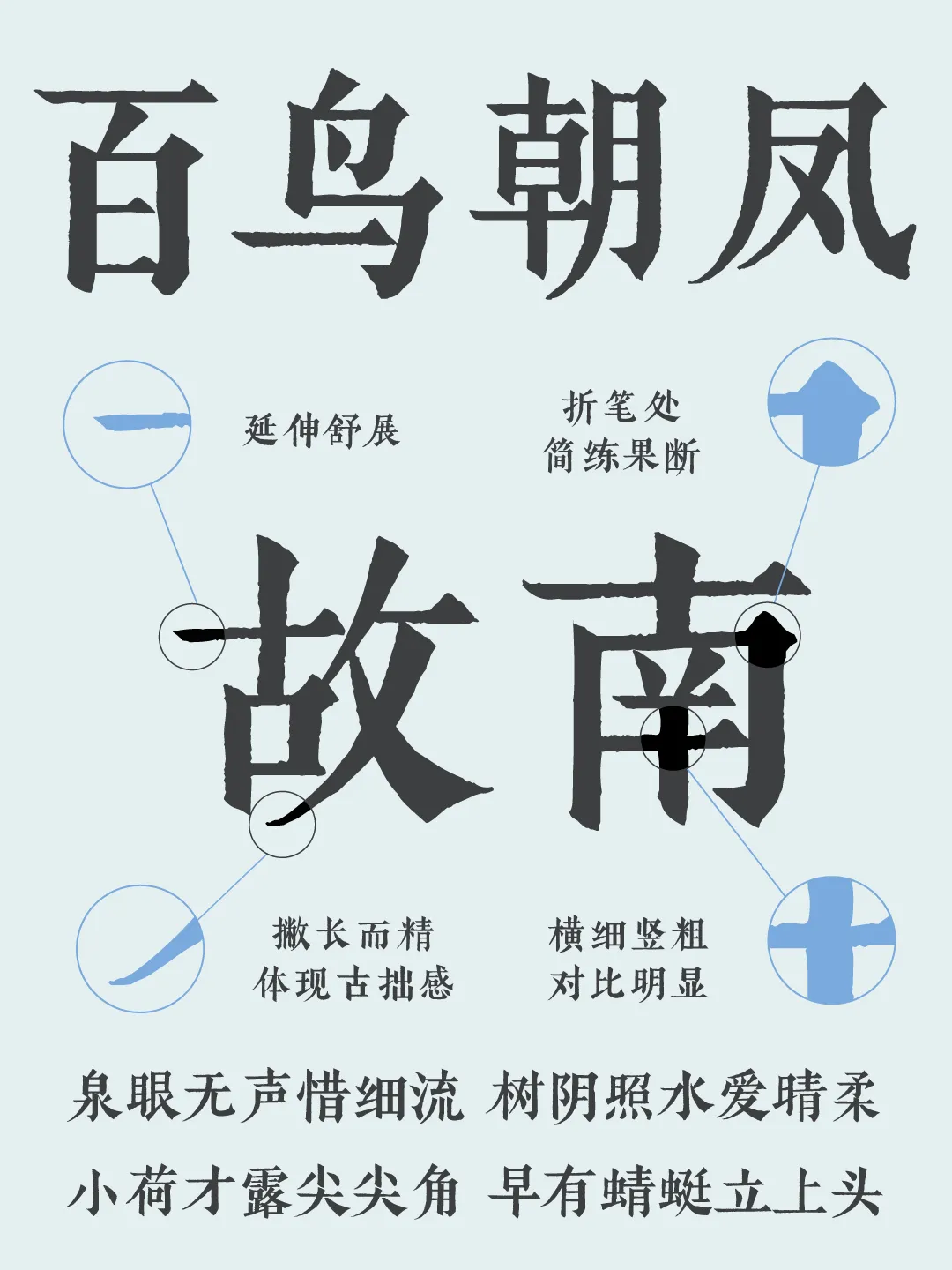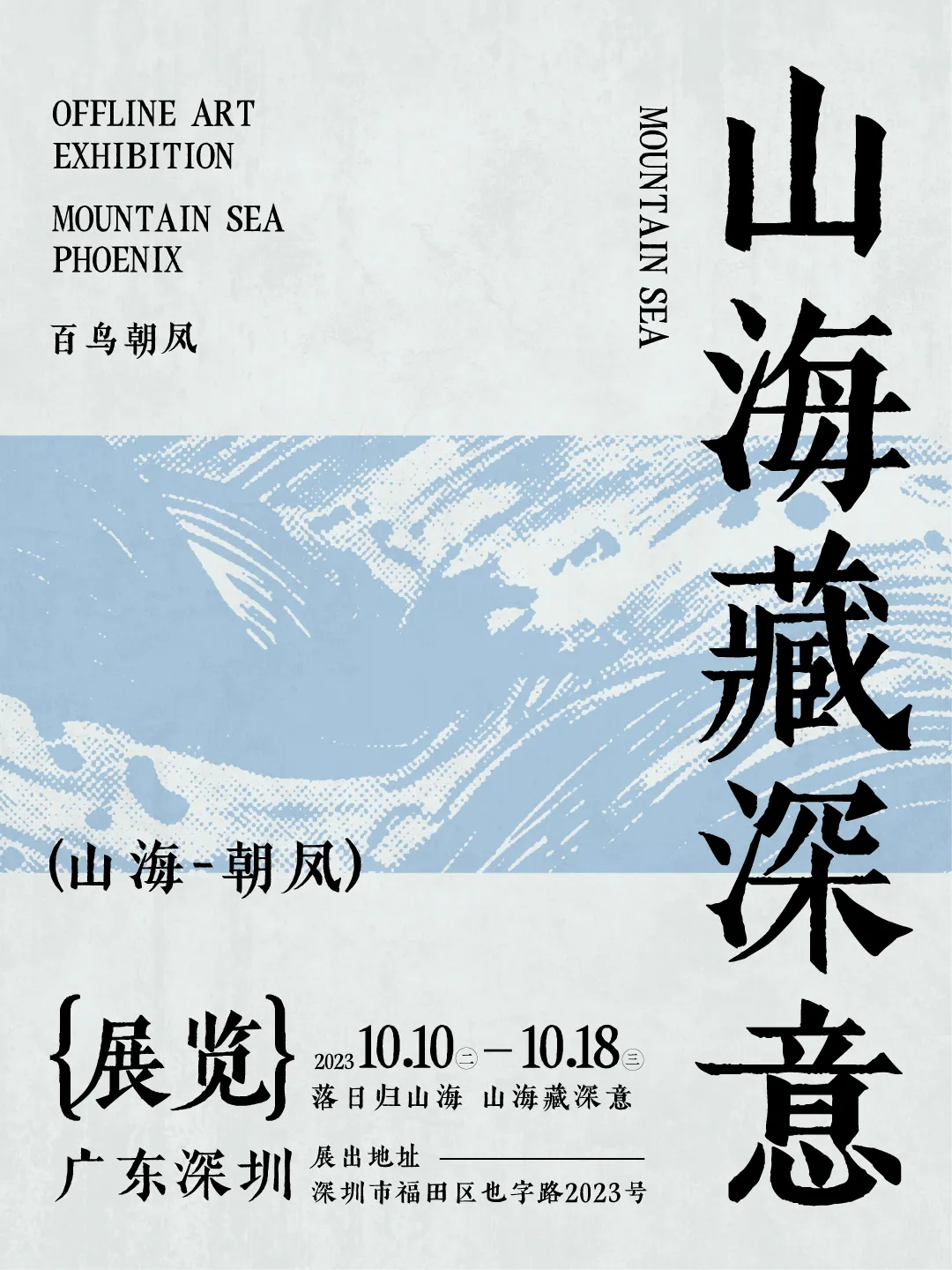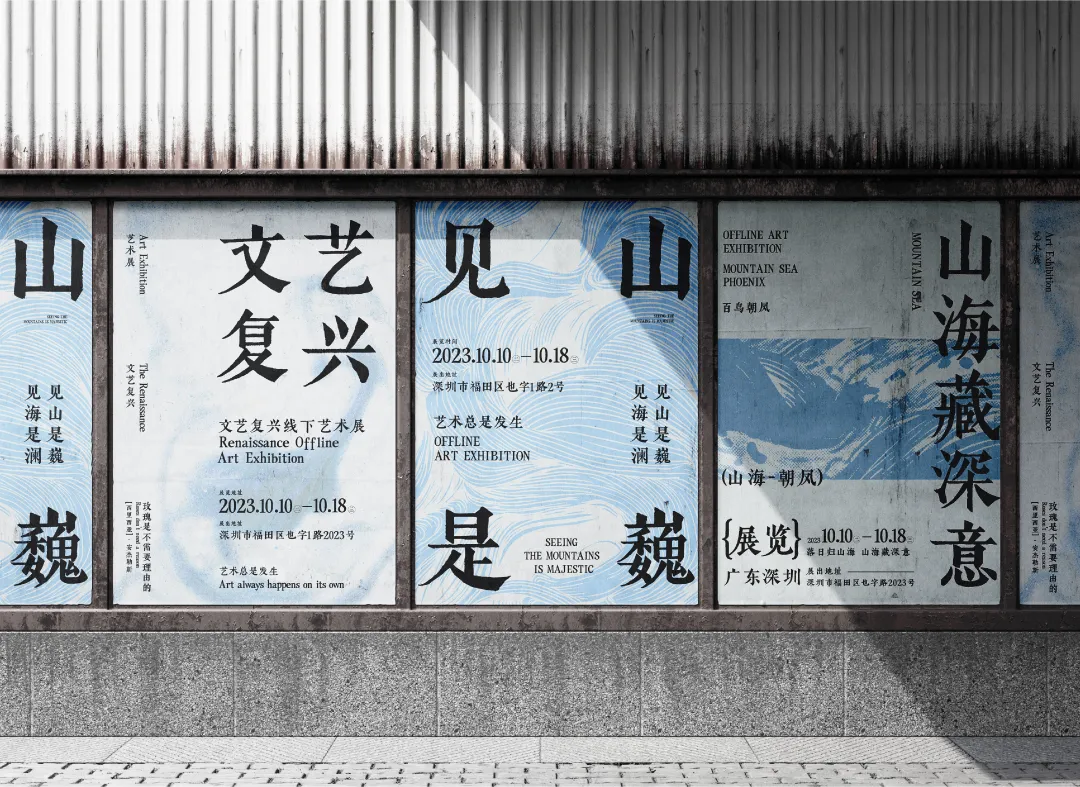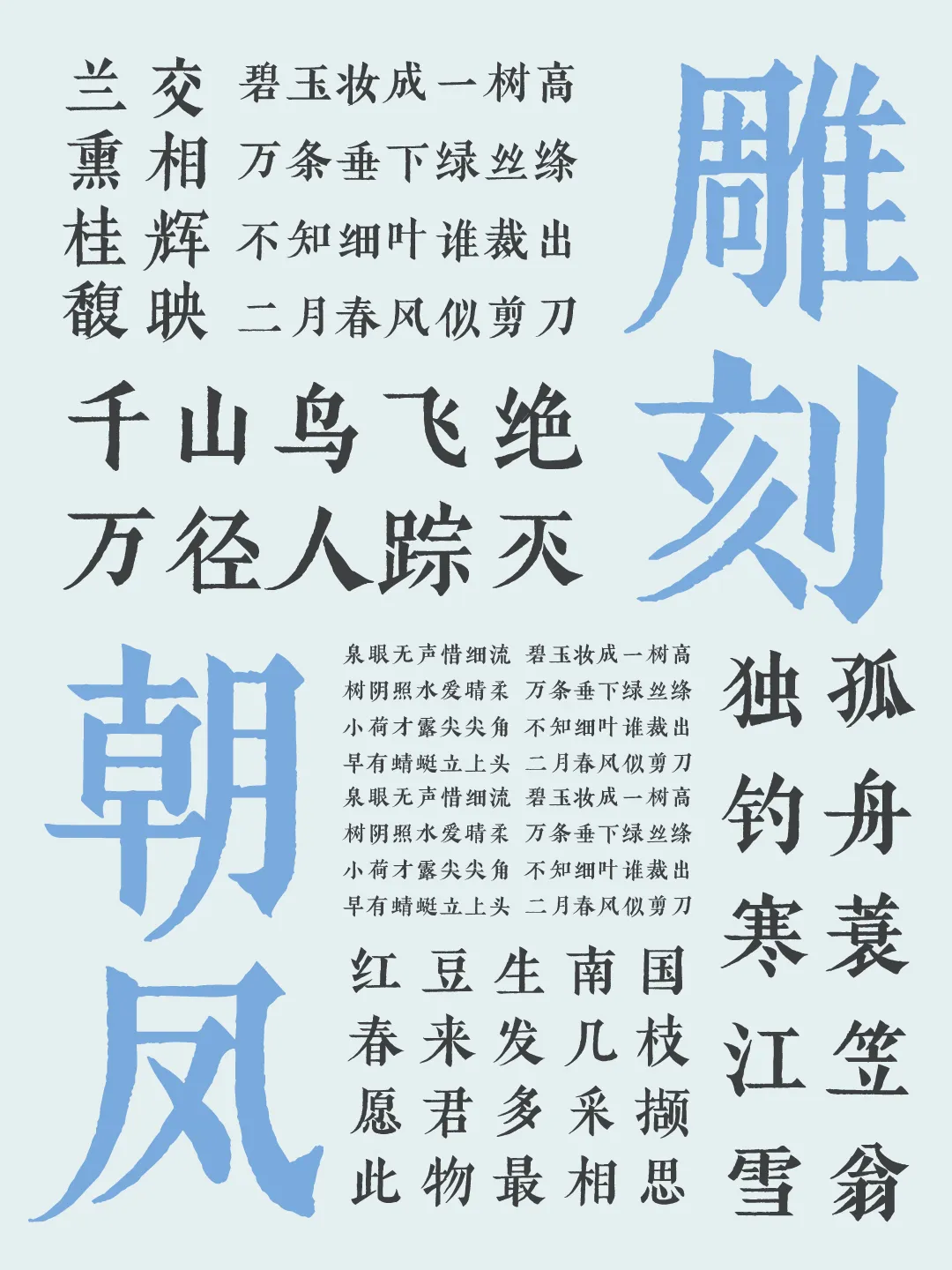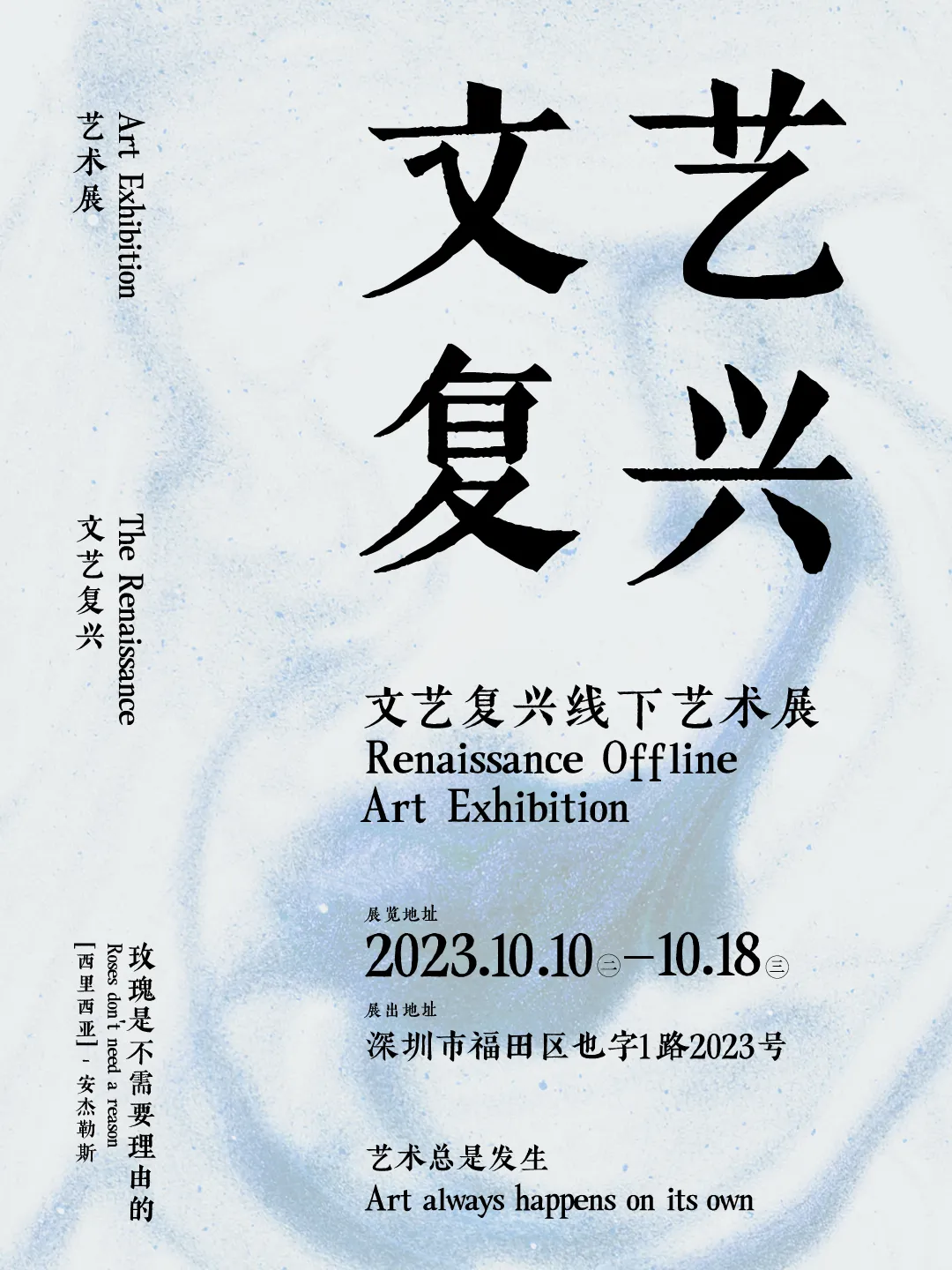
字圈也字山海朝凤宋
Cofont-YEchaofengGB
字圈也字山海朝凤宋选择了颜体作为刻书字体的骨骼,仍然保留横竖有粗细对比,横画末端 带有钝角等诸多宋体字的特征;
同时该刻本字迹清晰明了,风格气势雄强,点画沉实有力, 很好的体现了颜体书法凝重厚实的特点,在复古中又有一点变化,增添了一点活泼生动的感觉。